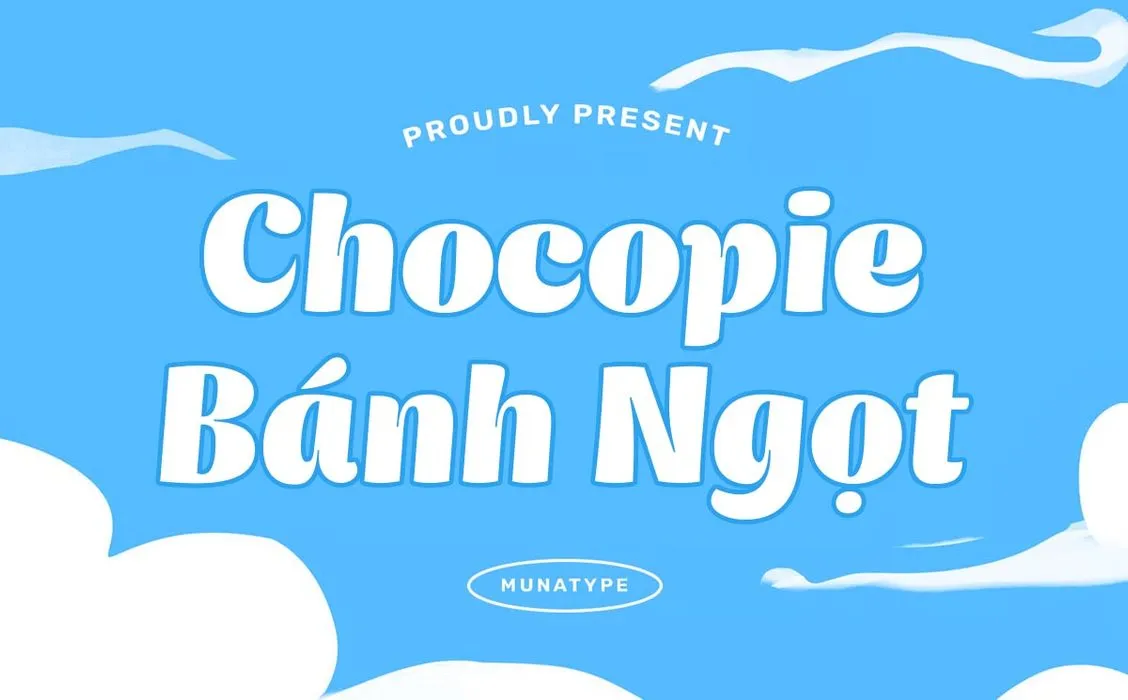
Nếu bạn đang tìm kiếm một phông chữ mang phong cách vui tươi, ngọt ngào và tiếp cận thị giác người xem một cách tự nhiên nhất, phông chữ miễn phí SVN Genica Pro chắc chắn là sự lựa chọn không thể bỏ qua. Bộ typography này nổi bật với những đường nét tròn trịa, mũm mĩm và cực kỳ đáng yêu, giúp các sản phẩm sáng tạo của bạn trở nên sinh động và tràn đầy năng lượng tích cực. Hãy cùng khám phá sức hút đặc biệt của bộ phông chữ Việt hóa ấn tượng này ngay dưới đây!
Phông Chữ Miễn Phí SVN Genica Pro – Nét Chữ Mũm Mĩm Đáng Yêu Bứt Phá Mọi Giới Hạn Thiết Kế
Trong thế giới thiết kế đồ họa đa dạng ngày nay, việc lựa chọn một phông chữ thể hiện được đúng thần thái của thương hiệu là yếu tố then chốt quyết định sự thành công của một chiến dịch truyền thông. Phông chữ miễn phí SVN Genica Pro nổi lên như một giải pháp typography hoàn hảo dành cho những ai muốn truyền tải sự thân thiện, gần gũi và vui vẻ. Được nâng cấp và Việt hóa tỉ mỉ từ phiên bản gốc nổi tiếng, SVN Genica Pro không chỉ giữ trọn tinh thần sáng tạo ban đầu mà còn mang đến khả năng hiển thị tiếng Việt mượt mà, chuẩn xác đến từng chi tiết nhỏ.
Dù bạn là một designer chuyên nghiệp đang thực hiện các dự án nhận diện thương hiệu cho ngành hàng trẻ em, thực phẩm, bánh ngọt, hay đơn thuần là một content creator muốn tạo ra những bức ảnh quote ấn tượng trên mạng xã hội, SVN Genica Pro đều có thể đáp ứng một cách xuất sắc. Nét chữ mềm mại kết hợp cùng cấu trúc mũm mĩm độc đáo giúp bộ font này dễ dàng chinh phục ánh nhìn của khách hàng ngay từ giây đầu tiên.</p>
1. Đường Nét Mềm Mại, Bo Cong Mũm Mĩm Đầy Cuốn Hút
Điểm đặc trưng đầu tiên khiến phông chữ miễn phí SVN Genica Pro thu hút người nhìn chính là hình dáng chữ bo cong vô cùng tinh tế. Các góc nét được xử lý mềm mại, tạo nên cảm giác tròn trịa, dày dặn nhưng lại không hề gây nặng nề hay thô cứng. Kiểu dáng mũm mĩm này mang đến sự ấm áp, dễ chịu và gợi mở cảm xúc thân thiện, thích hợp để kéo gần khoảng cách giữa thương hiệu và người tiêu dùng.</p>
Sự cân bằng tỷ lệ giữa các nét thanh nét đậm trong SVN Genica Pro được tính toán kỹ lưỡng, giúp văn bản giữ được sự rõ ràng dù hiển thị ở kích thước lớn trên biển hiệu hay kích thước nhỏ trong bài viết mạng xã hội. Đây chính là yếu tố làm nên tính nghệ thuật cao cho phông chữ này.
2. Bộ Ký Tự Việt Hóa Hoàn Chỉnh, Chuẩn Xác Từng Đường Nét
Một trong những điểm cộng lớn nhất của SVN Genica Pro chính là bản Việt hóa chất lượng cao do đội ngũ SVN thực hiện. Tất cả các dấu thanh, dấu phụ trong tiếng Việt như sắc, huyền, hỏi, ngã, nặng, cũng như các chữ cái đặc trưng (ă, â, đ, ê, ô, ơ, ư) đều được thiết kế tỉ mỉ, đồng bộ hoàn toàn với phong cách tổng thể của bộ font gốc.
Người dùng sẽ không gặp phải tình trạng lỗi font, đứt nét hay khoảng cách dấu bị lệch – những sự cố vốn rất phổ biến khi sử dụng các phông chữ nước ngoài chưa được tối ưu cho tiếng Việt. Nhờ đó, quy trình làm việc của nhà thiết kế được rút ngắn tối đa, đảm bảo tính chuyên nghiệp và thẩm mỹ vượt trội cho toàn bộ tác phẩm.
3. Khả Năng Ứng Dụng Đa Dạng Trong Nhiều Lĩnh Vực Thiết Kế
Phông chữ miễn phí SVN Genica Pro thể hiện tính linh hoạt tuyệt vời khi có thể ứng dụng trong vô số dự án truyền thông và nghệ thuật thị giác khác nhau:
- Thiết kế bao bì sản phẩm: Phù hợp cho các ngành hàng thực phẩm, đồ uống, bánh kẹo, mỹ phẩm thiên nhiên và các sản phẩm dành riêng cho mẹ và bé.
- Truyền thông Mạng xã hội: Tạo điểm nhấn thu hút cho banner quảng cáo, hình ảnh bài viết trên Facebook, Instagram, TikTok hay thumbnail YouTube.
- Ấn phẩm xuất bản: Làm tiêu đề sách thiếu nhi, truyện tranh, tạp chí phong cách sống hoặc thiệp chúc mừng, thiệp mời sự kiện.
- Nhận diện thương hiệu: Thiết kế logo, slogan hoặc biển hiệu cho các quán cafe, tiệm bánh, cửa hàng thời trang trẻ em mang phong cách đáng yêu, ngọt ngào.